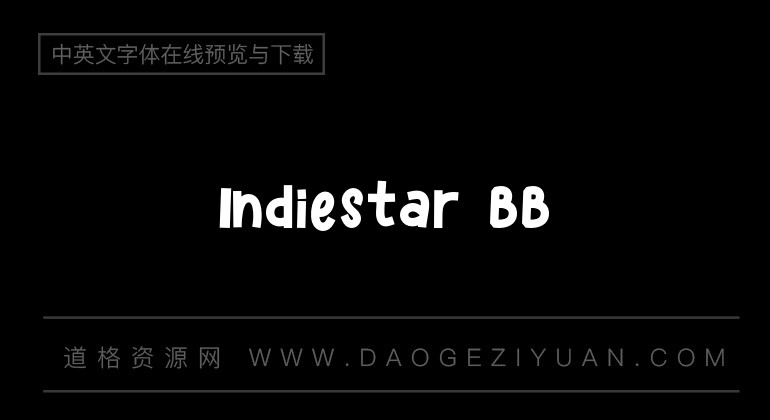
IndieStar BB 是一种手写风格的字体,具有独特的个性和艺术感。该字体由设计师 Nate Piekos 创作,旨在提供一种同时具有手工制作感和现代风格的字体。 IndieStar BB 的特点包括: 1. 手写风格:该字体的字形仿照了手写字母,带有自然而不规则的笔画和线条,让文字看起来更加生动、有趣。 2. 清晰易读:尽管是手写风格,IndieStar BB 的字母和数字仍然非常清晰易读,也适合在小字号下使用。 3. 独特个性:IndieStar BB 具有很强的个性,适合用于标志、海报、散文和其他需要突出品牌个性和特色的设计项目。 总之,IndieStar BB 是一款独特的、具有艺术感的手写字体,适合用于各种设计项目中。内容介绍
IndieStar BB是一款非常不错的手写艺术字体,具有很好的视觉感,适合于文化类的宣传设计、商业类品牌的广告和产品包装设计以及个性化文字排版等较多场景。